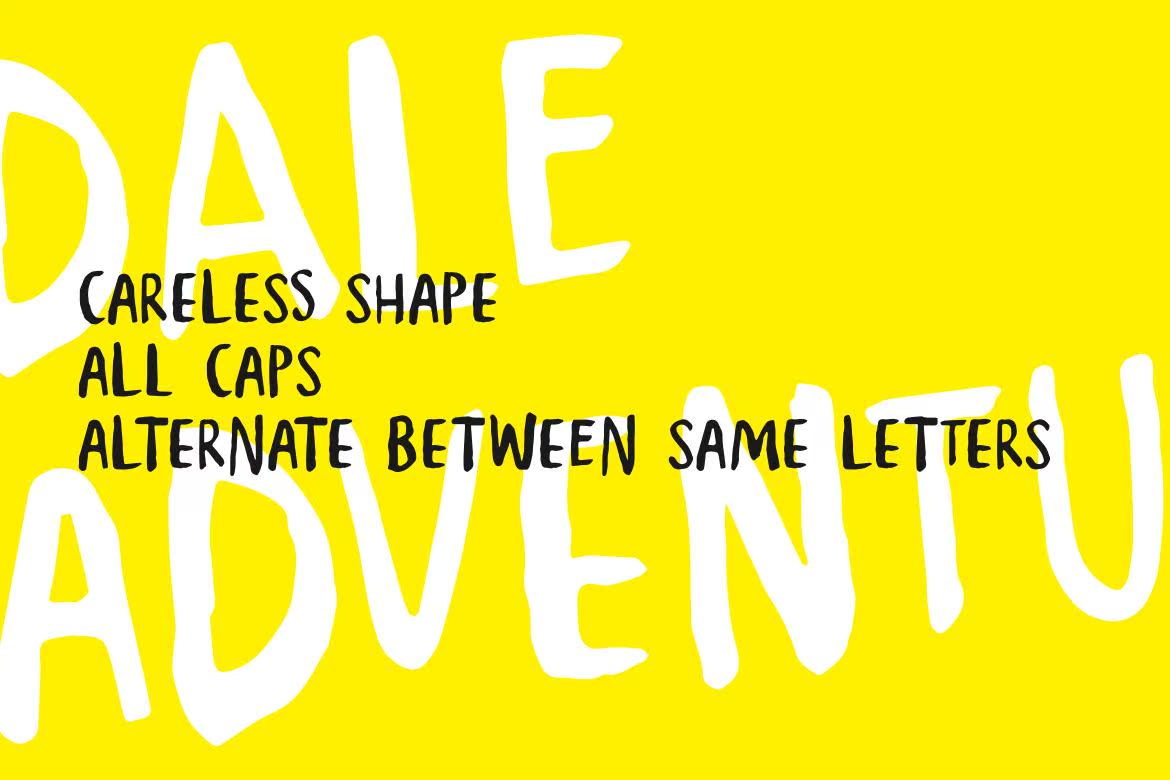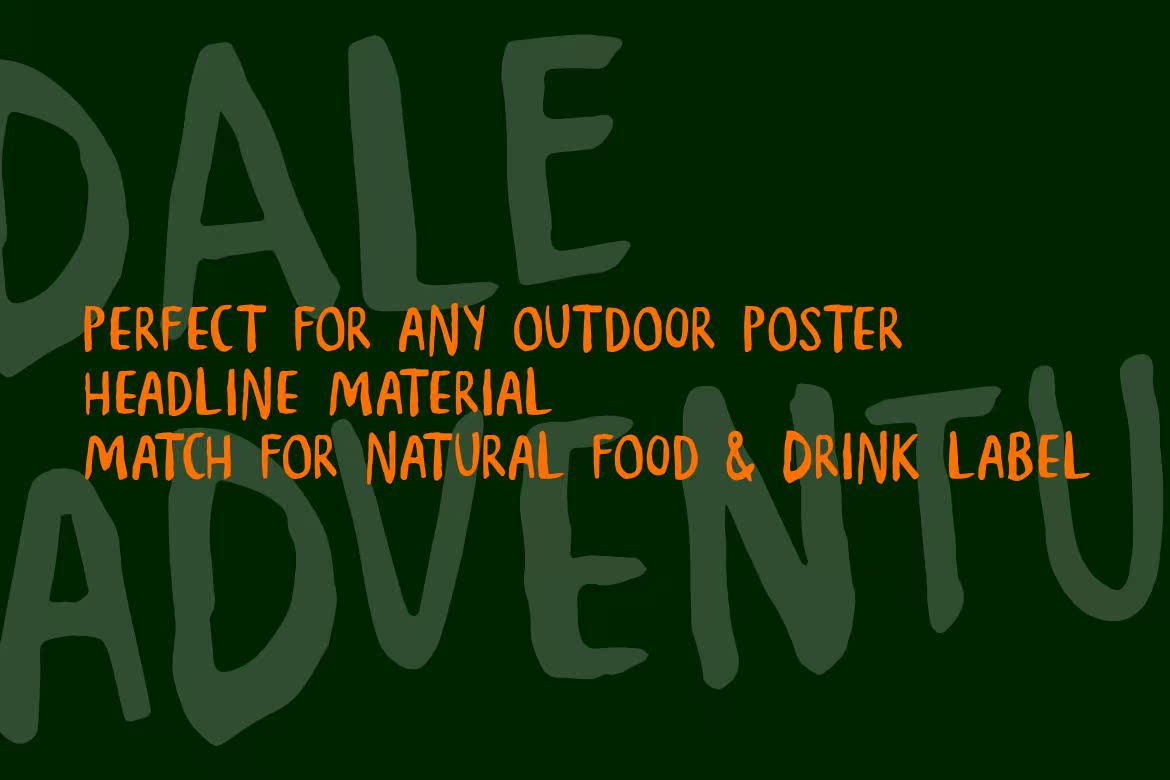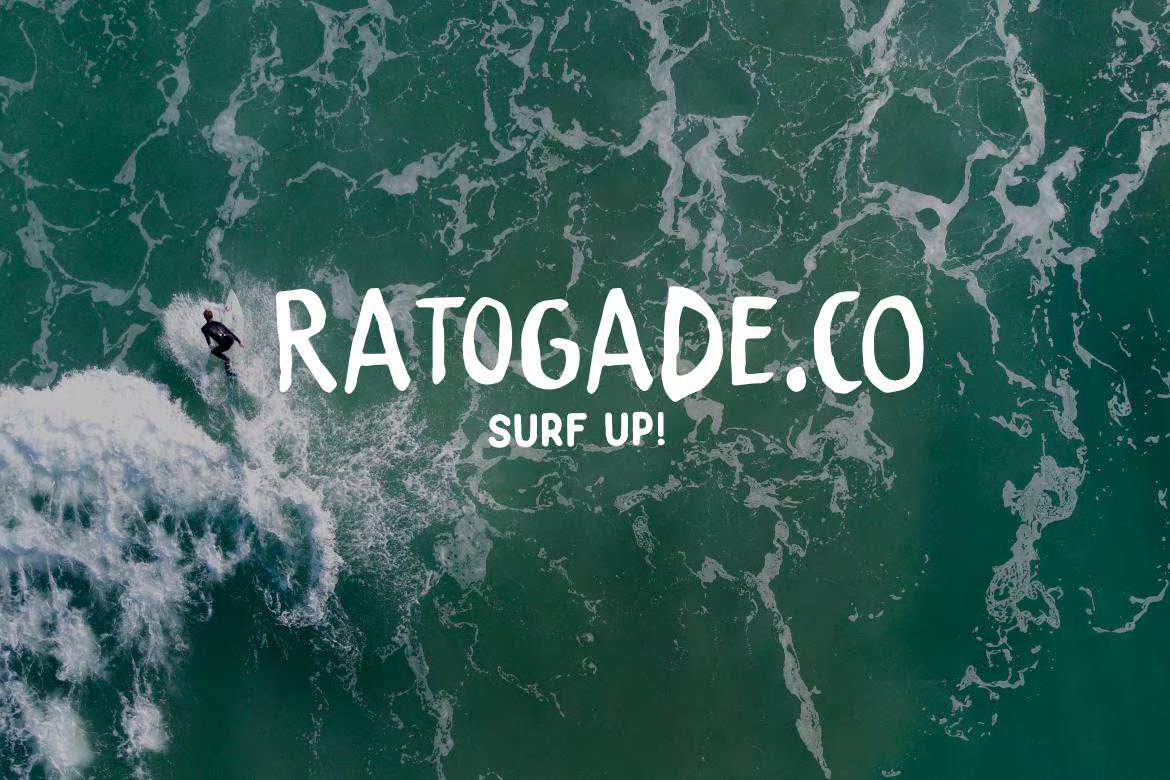
像我一样,Dale Adventures带来了巨大的能量去探索野外。没有人走过的路,没有人接触过的丛林,你说的就是。Dale Adventures现在已经不太可能到达这里了。所有大小写之间的变化都会让你的书写看起来更加自然。更不用说两个元素之间什么时候彼此相邻……它们是魔法笔。像我一样,Dale Adventures带来了探索野外的巨大能量。你可以说,没有人走过的小径,没有人接触过的丛林。Dale Adventures很快就会来到这里。所有大小写之间的变化都会让你的写作看起来更加自然。更不用说两个元素之间是否相互靠近……这就是Magicapen。